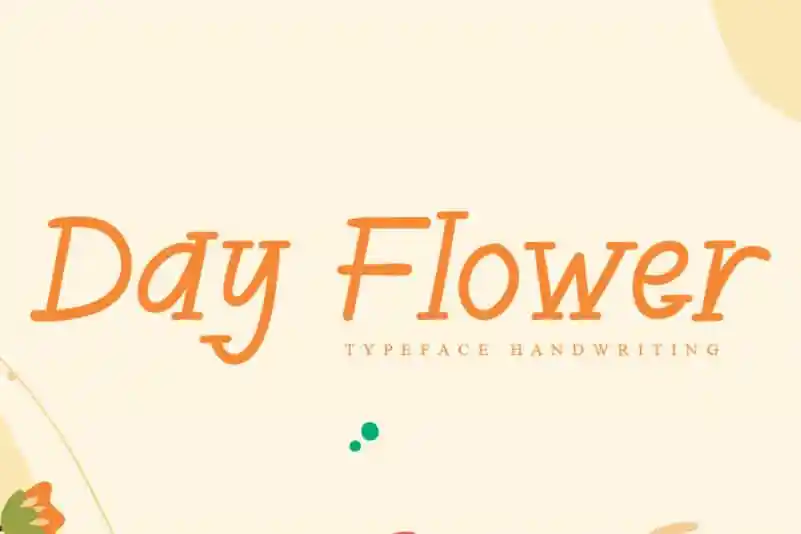
Day Flower Display Font – Fonte Grátis
Day Flower Display Font
A fonte Day Flower Display Font é uma delicada e agradável escolha para aqueles que apreciam a mão-dura criativa. Seu estilo natural e único se encaixa perfeitamente em uma variedade de designs, estendendo o seu potencial além da imaginação dos designers. Sua elegância e personalidade singular torna-a uma opção versátil para gráficos digitais, desde logotipos e letras do título até elementos de design de página web. Se você está buscando um recurso gráfico com a capacidade de expressar sua criatividade através de uma fonte handwritten única, Day Flower Display Font é uma opção perfeita. Com ela, seu trabalho ganha vida e se torna ainda mais especial.